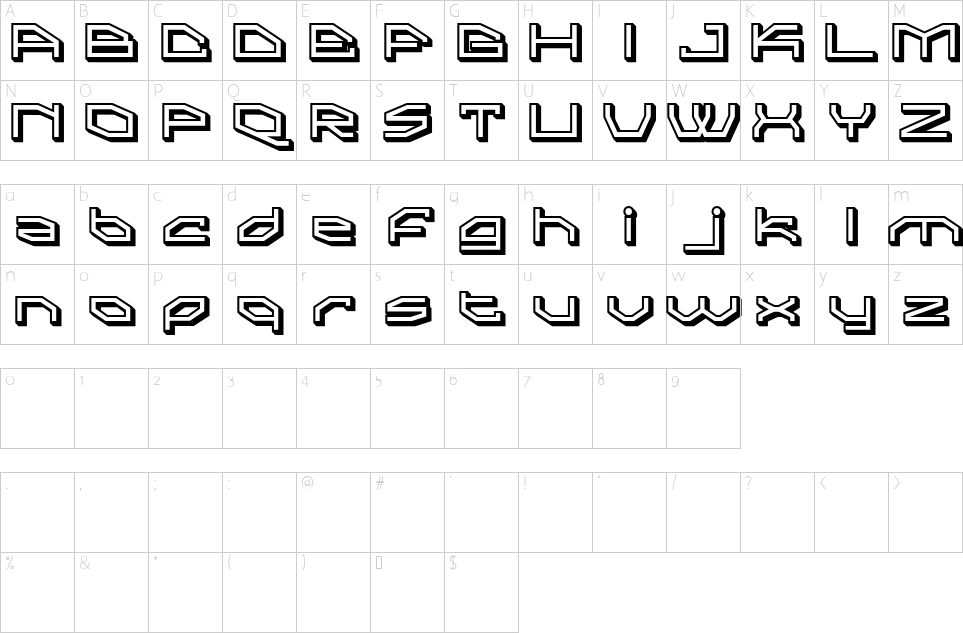
Descubra a beleza única e versátil do Gefalent Font para seu próximo projeto. Esta elegante fonte foi criada pelo Craft Supply Co, oferecendo uma variedade de opções para personalizar qualquer layout ou design digital. Através deste download gratuito, você pode experimentar seus diferentes tipos, tamanhos e ajustes, tornando a Gefalent uma escolha perfeita para designers gráficos que valorizam um toque único em seus trabalhos. Com sua simplicidade sofisticada e estilo distintivo, o Gefalent está disponível tanto para os usuários de Windows quanto para aqueles de Mac. E se você é uma das muitas pessoas que já experimentaram a beleza desta fonte, não se esqueça de dizer em qual projeto ela foi usada e compartilhar sua experiência conosco!